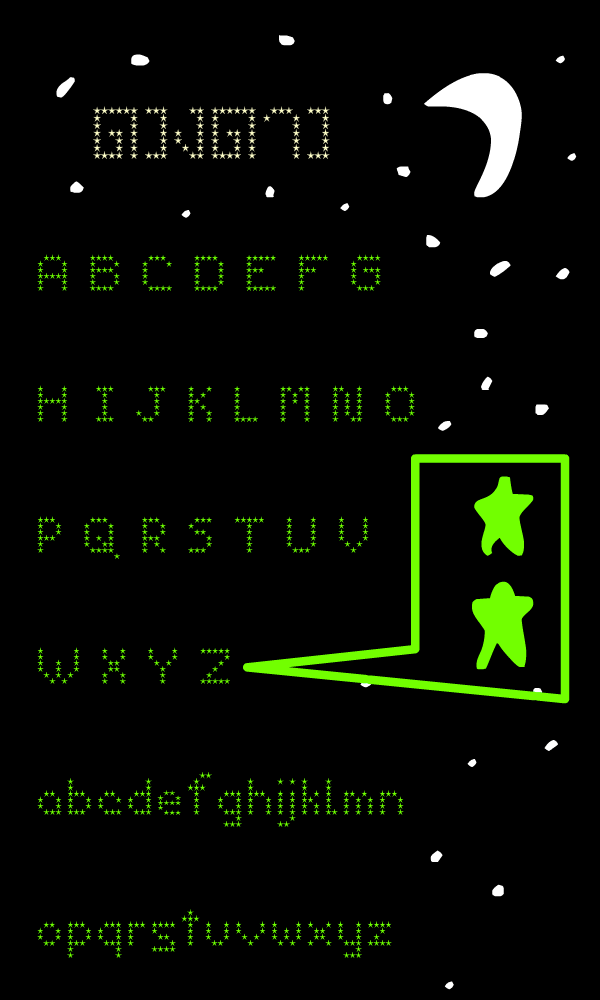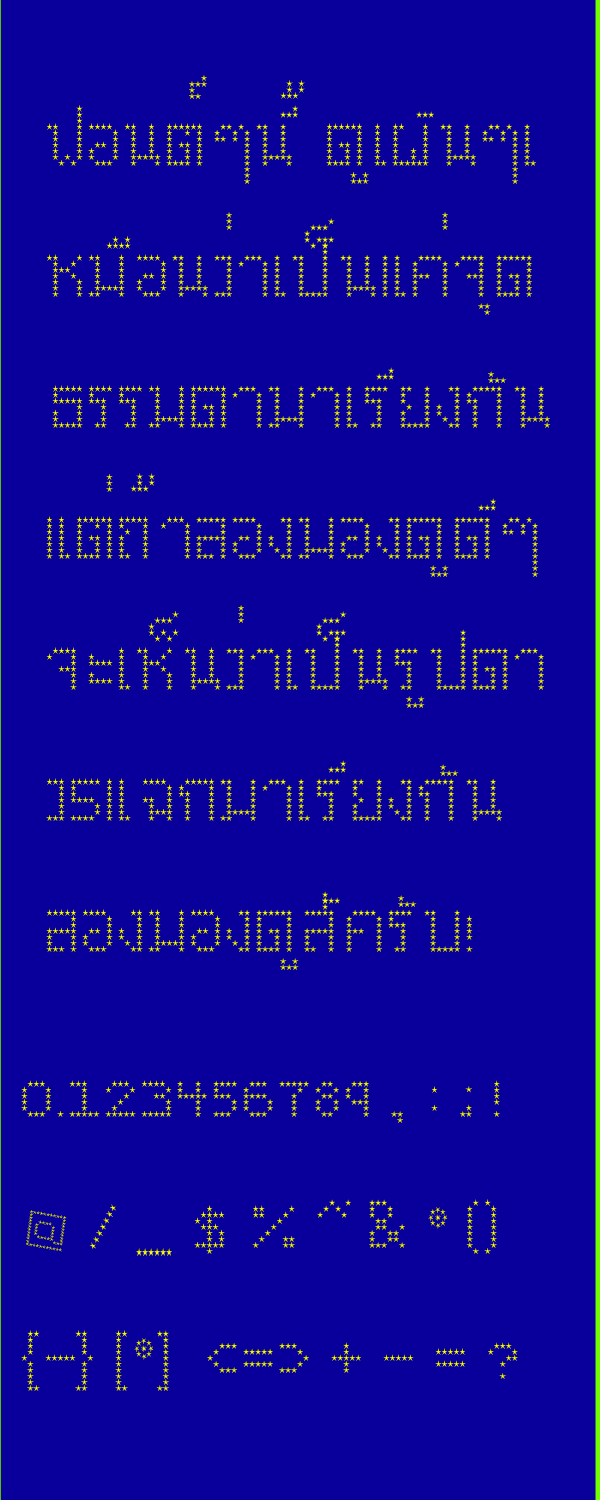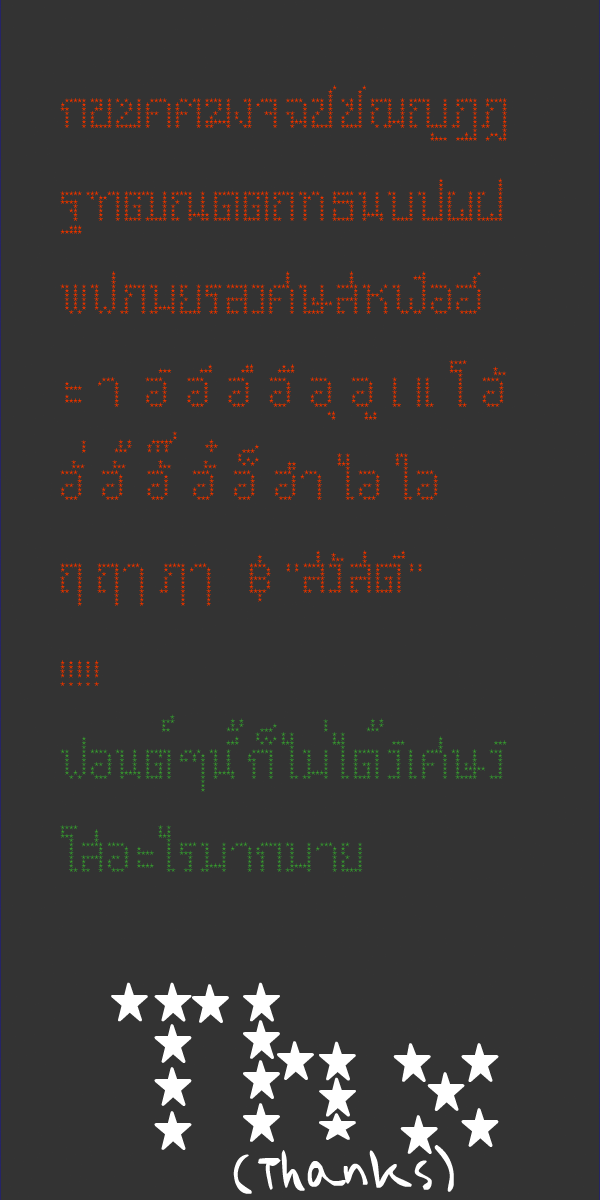
2015_DuangDao (ดวงดาว)
ยะเห้!! ปิดเทอมก็ปิดแล้ว การบ้านก็จบแล้ว เวลาว่างก็มาถึง ลองออกไปที่ระเบียงแล้วแหงนหน้าขึ้นไปบนท้องฟ้าในคืนที่ฟ้าโปร่งในเวลาประมาณสองทุ่ม ดวงดาวระยิบระยับประดับประดาบนท้องฟ้าในอวกาศอันกว้างใหญ่ที่แสนมืดมิด ดาวดวงนิดกะพริบๆ เหมือนส่งข้อความถึงกันด้วยรหัสมอร์สที่แสนจะยุ่งยากมากมาย
พอแหงนลงมาด้านล่างของระเบียงก็เห็นชีวิตความวุ่นวายของคนในกรุงเทพมหานครฯ ผู้คนเดินขวักไขว่ซื้อของกันมากมาย มีเสียงรถตุ๊กๆ และมอเตอร์ไซค์บีบแตรใส่กัน มีลมเย็นๆ พัดผ่านใบหน้าของฉัน ชวนให้รู้สึกดี พอแหงนหน้าขึ้นไปบนท้องฟ้าอันมืดมิดใหม่อีกครั้ง ก็เจอดวงดาวส่งรหัสมอร์สหากันเช่นเคย มีพระจันทร์เหมือนเป็นแม่คอยดูแลดวงดาวเหล่านั้นอยู่ห่างๆ แหงนหน้าออกไประเบียงซักครู่ น้ำค้างลงจัด เดี๋ยวจะเป็นหวัด เดินออกจากระเบียงกลับเข้าห้อง แล้วก็เกิดนึกไอเดียมาว่า “น่าจะเอาดวงดาวเหล่านี้มาทำฟอนต์เป็นรูปดาว 5 แฉก” (สาบานได้ว่าไอ้ที่เขียนไปเมื่อกี๊ไม่ได้เมากาวไปเขียนไป)